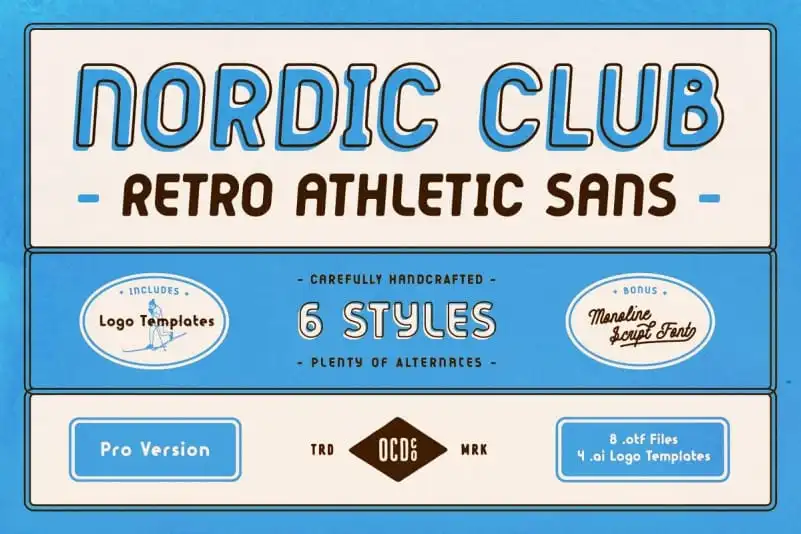
Nordic Club Sans Serif Font – Download Grátis
Nordic Club Sans Serif é uma fonte moderna que traz aos designers e criadores de design a oportunidade de incorporar uma elegância arquitetada para suas criações digitais. Inspirada nas práticas esportivas inverno, como a natação e as atividades de esqui, esta fonte apresenta linhas retas com um toque suave de curvas vintage e clássicas que combinam a robustez moderna e o glamour nostálgico. Ideal para criar design gráfico atemporal e contemporâneo, Nordic Club Sans Serif é perfeito para se integrar em cartazes, logotipos, banners e outros elementos visuais onde um toque de elegância clássica e uma atmosfera suave mas moderna podem trazer ao seu trabalho. Em cada letra e conjunto, a fonte evoca o encanto da prática esportiva inverno, transmitindo a sensação de seriedade e desafio que acompanha atividades como as natação e o esqui. Esta fonte é um marco em sua categoria, celebrando não apenas a beleza da linha reta e modernidade, mas também uma paixão pela prática esportiva inverno.